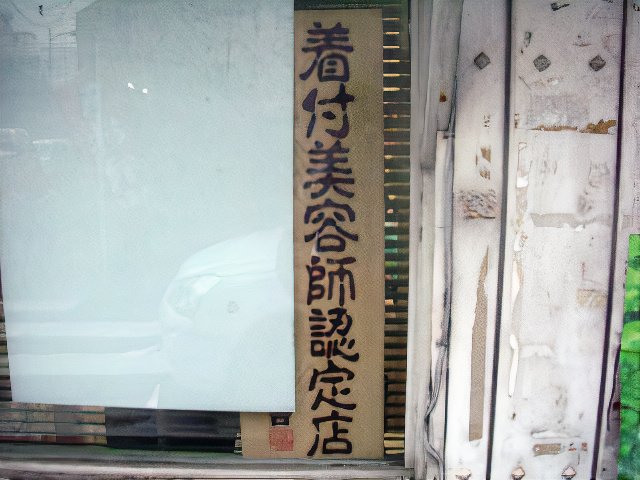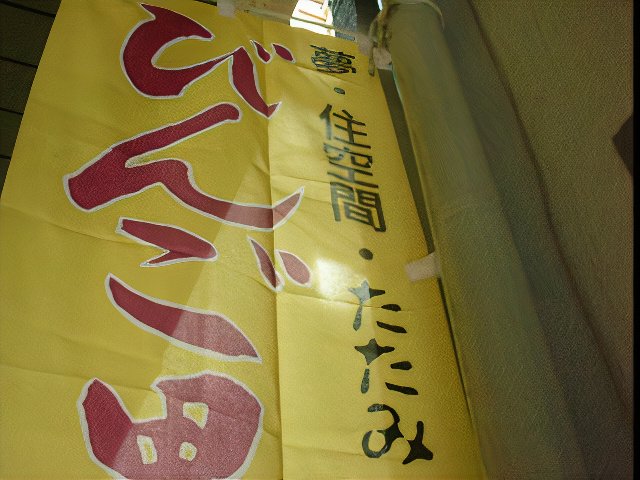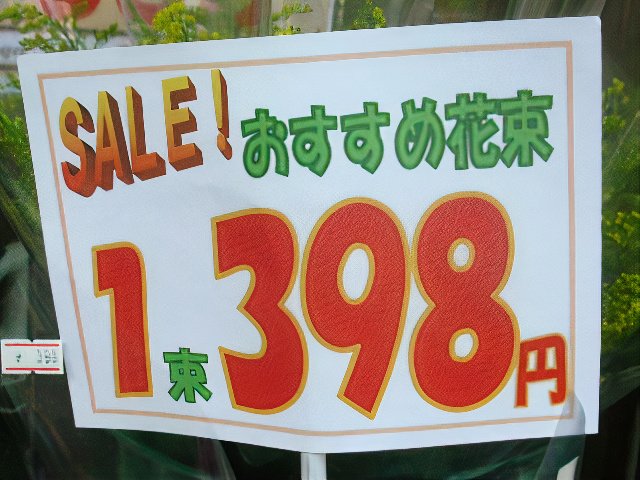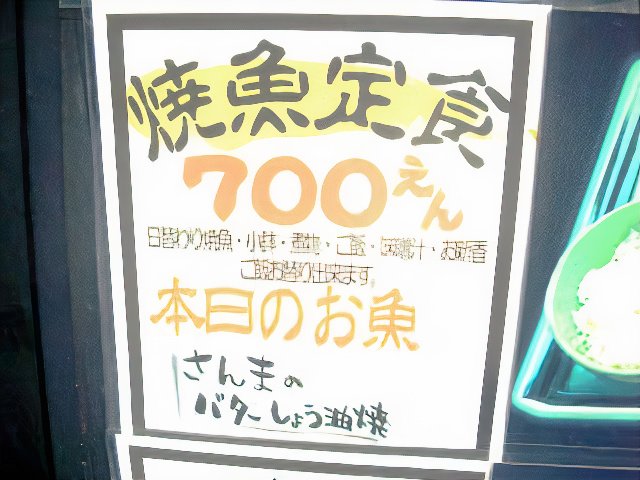
パソコンの普及で、昔に比べて手書きの文字を書く機会がずいぶん少なくなった。僕みたいに悪筆な人間にもやさしい時代の到来だ。
でも、だからといって気を抜いてばかりもいられない。悪筆問題をやりすごした先には、パソコン特有の問題「フォント選び」がたちはだかっている。するとこんどは「フォントを選ぶ」という新たな自由が生まれた。
しかし世の中には、そんな問題が潜んでいることにまったく気づかないで書かれてしまった文字がある。自由を与えられても人はえてして無難なフォントを選んでしまいがちだが、中には独特のフォント選びにより何とも言えない「味」が生まれてくる場合がある。今日はそんな文字たちを鑑賞していきたい。
不適切な味のあるフォントづかいとは?
まずは下の画像を見てほしい。
花屋さんのポップだ。注目してほしいのは、数字に使われているポップ体。文字のウキウキした感じにつられて、私も1束買っていこうかしら、なんて気分になってしまう。うまいフォントづかいだ。
しかし、これはどうだろう。
おかたい資料に、うかれた文字。TPOをまったく意識していないフォント選びだ。この資料で予算達成状況の説明をされても、半笑いで説明されているみたいでぜんぜん説得力がない。
フォントなんて何を使っても自由だけれど、文書の内容に応じて向き・不向きがあるのは確か。ゆえに、このようにどうしてもしっくりこない、「それ違うよ!」といいたくなるフォントづかいが生まれてしまうのだ。
例えば、この写真を見てほしい。
「その時の気分でかみつきます」と、かなり深刻な警告が丸文字でコロコロと書かれているので思わずなごんでしまった。これが内容とフォントのギャップで発生している「味」である。
そんな間違った味のあるフォントづかいを集めて、分類した。ポップ系、ホラー系、3D系、その他、の4種類だ。順に紹介していこう。
ポップ系
まずは定番のポップ系からだ。
世の中にあふれている間違った味のあるフォントづかいのなかでも、いちばんよく見られるのがポップ体。会社で、街で、お店で、駅で、いたるところでTPOをわきまえてないポップ体を見ることができる。Microsoft Officeに入っているので、気軽に使いやすいのだろう。今回は、定番のポップ体にくわえて、丸文字やまんがみたいな文字もポップ系に分類した。
ウキウキした文字は緊張感をそぐ。注意書きや、謝罪文、警告にはもっとも向かないフォントだと組み合わせると味わいが生まれがちだ。
🖋️強い表現を削除し、ポジティブにしました。また、ポップ体に対するツッコミはありがちなネタなので、このセクションごと削ることも検討したいです。
🖋️昔のマンガっぽい文字を適当に「手塚治虫」と言っていませんか?
ポップ系の中でも、いちばん浮き足立っている浮かれているのはやはり丸文字。猛犬注意がまったく緊張感をかもしださないのはもちろん、営業時間案内ですら、ちょっと信用できない印象なのだ。猛犬注意からも営業時間案内からも、ついついウキウキが漏れ出てしまう。
TPOのわきまえてなさ、空気の読めてなさこそが、ポップ系のフォントづかいの醍醐味といっていいだろう。
ホラー系
意外に多いのがこのホラー系。インクが途切れるように、太い部分と細い部分が混在する文字たち。なんとなく人に恐怖心を呼び起こさせ、不安にさせるフォントだが、うっかり食べ物なんかに気軽に使われていることが多い使われると別の味わいが出てくる。
特徴のあるフォントだけに、個性的なフォントを使おうと思った人がうっかり手を伸ばしてしまうのかもしれない。これが恐ろしい文字であることに気づかないままに。
しかし、これは地雷だ。うっかり踏んでしまったら一気に紙面全体がどんよりと霊気に包まれる。万全の注意を払いたい。
個性的なフォントだけにいろいろ想像が広がってしまう字体たちである。